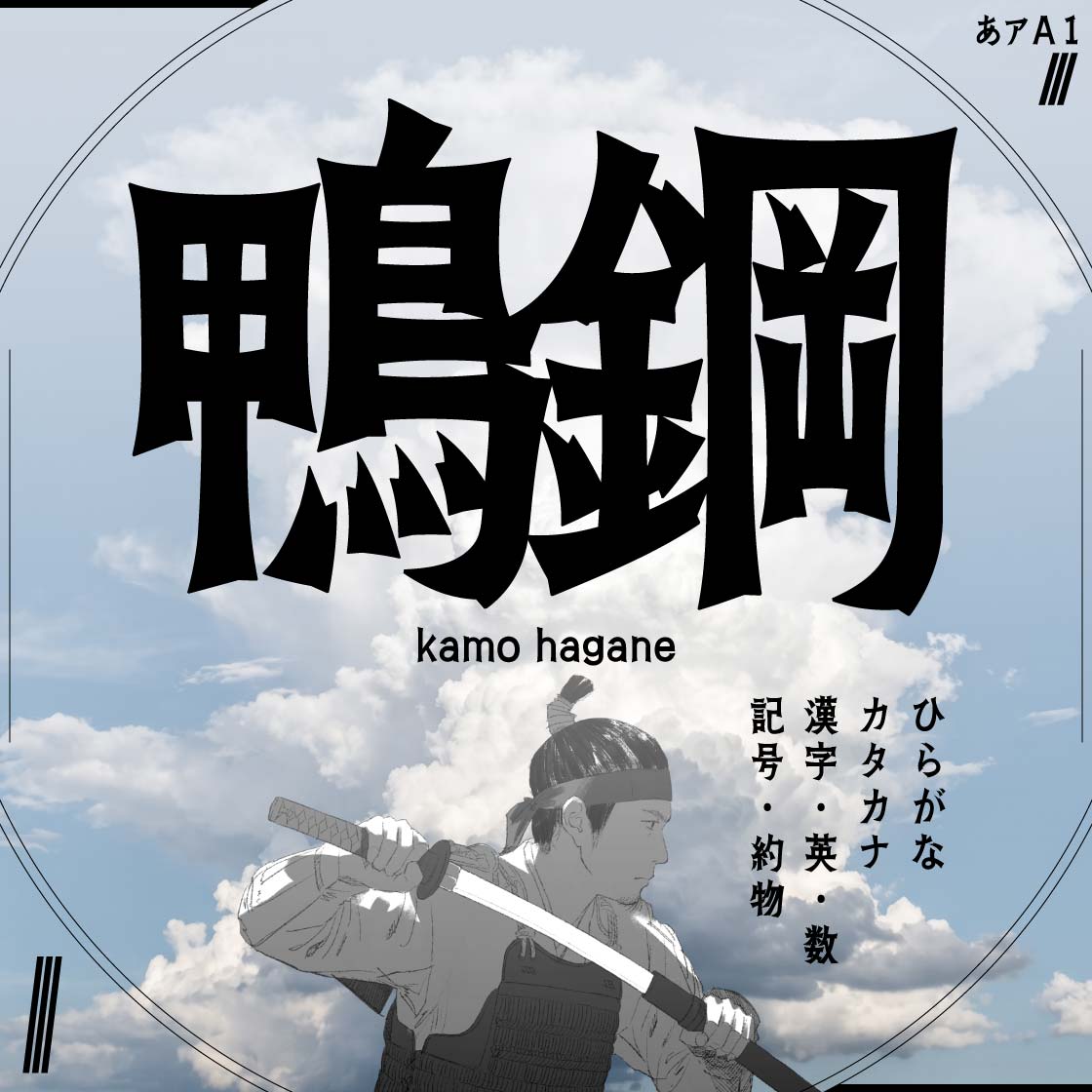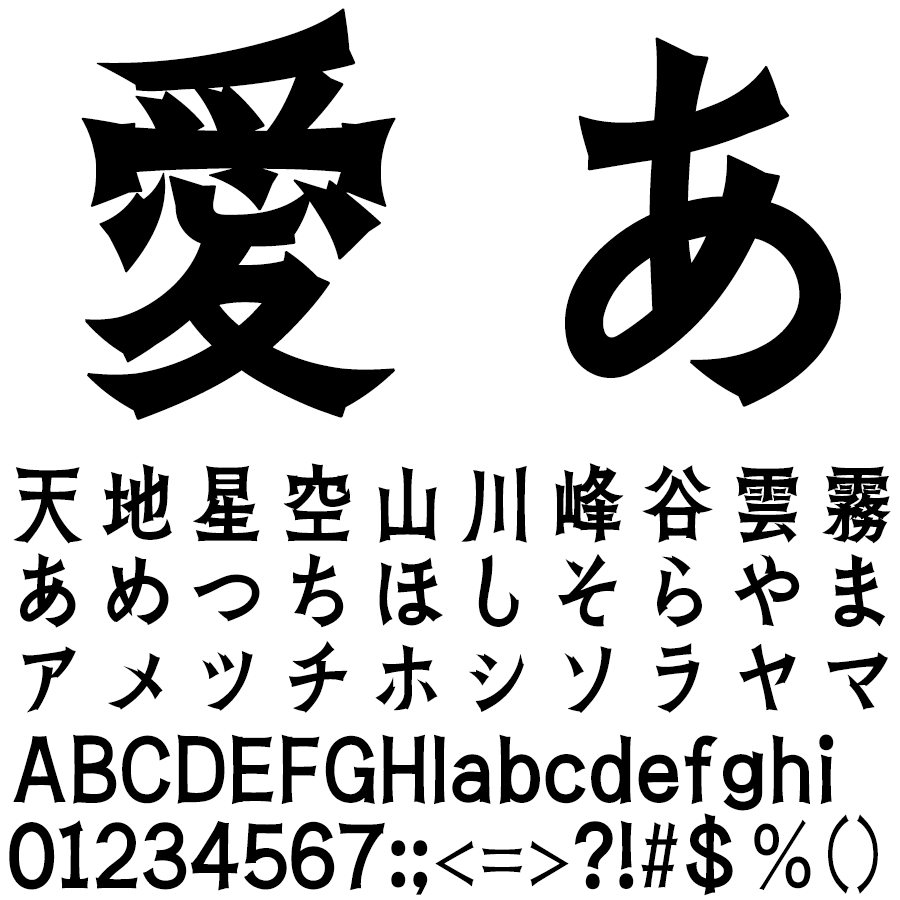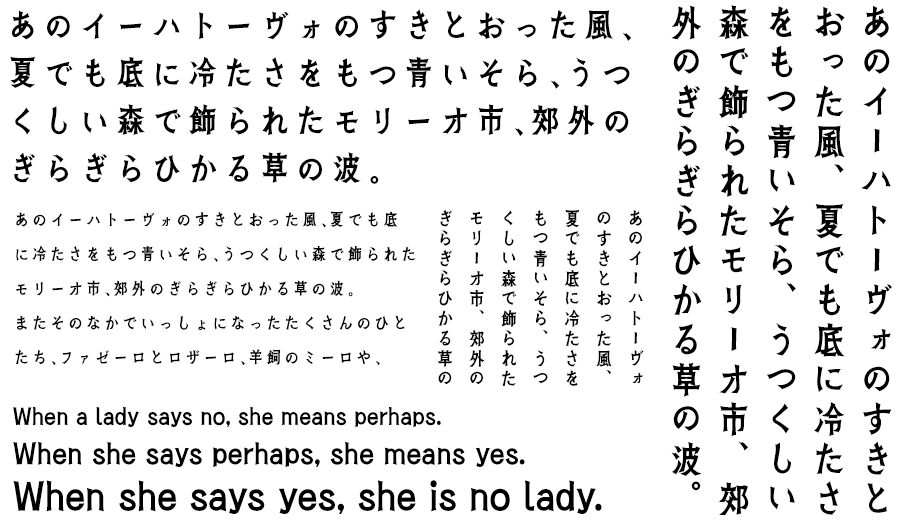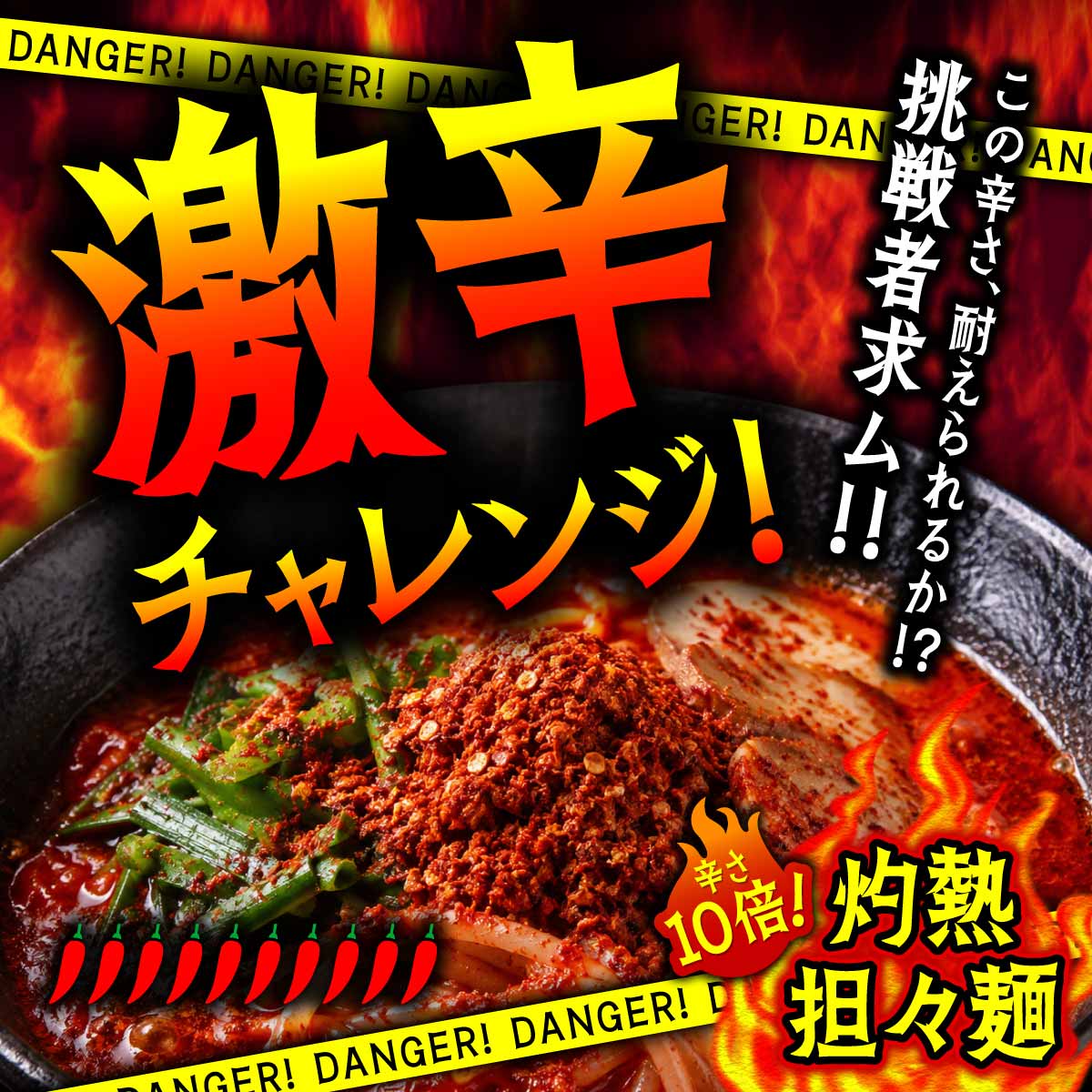
なにも無いところから、なにかを作りたい。今あるモノをもっと良く見せたい。お客様から寄せられる様々な課題をデザインという視点から観察し新たな発見や問題の解決、違った見え方や驚きある体験をご提案することをコンセプトとする「ヤマナカデザインワークス」。
鴨鋼 (かもはがね)
「鴨鋼 (かもはがね)」は明朝体ではなく、筆文字でもない。しかし手書き感のある線運びを持たせることで、有機的な鋭さを表現した日本語フォントです。
スズメボンボン
「スズメボンボン」は、ヤマナカデザインワークスにとってのスタンダードとして制作した、コミカルで可愛く、扱いやすい日本語フォントです。
ネコノコラヂヲ
「ネコノコラヂヲ」は、レトロ・エレガンスをテーマとして、装飾的な猫脚をデザインソースに制作した日本語フォントです。今尚現代のクリエイターに影響を与え続ける「明治・大正」の頃のクリエイティブへの憧れを詰め込みました。見出しやタイトル、ロゴなどに是非お使いください。
ブルズドーナツ
「ブルズドーナツ」は、コロコロ転げ回るフレンチブルドックをイメージして作った日本語フォントです。見出しやタイトル、ロゴなどに丸くてかわいい印象を持たせたいときに是非お使いください。
ティラノゴチ
手書き文字をベースとして、やんちゃ小僧をコンセプトに作った元気系日本語フォントです。見出しやタイトル、ロゴなどにインパクトを持たせたいとき、力強く元気な印象を持たせたいときに是非お使いください。
金魚ランタン
ブラックレター体を日本語の文字として解釈しなおして設計した日本語フォント。欧文・数字は日本語での解釈を元に再設計しているので、本来のブラックレター体とはまた違った印象となっています。強く鋭い印象を持たせたいとき、世界観を強調したい時に是非お使いください。
やわらかドラゴン
力強くもあり、どこか柔らかい。そんなイメージの日本語フォントです。インパクトを持たせたい時、優しい印象を持たせたい時に。色々な使い方を試してみてください!
かなりあ
かなりあは小さくコロコロとした小鳥のイメージで、字体を崩しすぎず、あらゆる場面で使えるシルエットを目指し作成しました。少し真面目で、でもかわいい日本語フォントです。
ぱぐのみんちょ
ぱぐのみんちょはゆるい感じの日本語フォントです。全グリフが変則的なサイズをしているので、仮名はプロポーショナル化してベタうちした際になるべく自然に見えるようにしています。
プぷプ
プぷプは、ちょっとかわいい、だいぶ丸いフォントです。小学校で習う漢字1000文字を収録しているので、日常会話程度はカバーできます!元々コミックのタイトル用に作成したフォントですので、タイトルや見出し、注目してほしい部分に効果的にご使用いただければと思います。
きなりゴシック
きなりゴシックは華奢で有機的なシルエットのフォントです。日本的でささやかな線表現を出すために作成したフォントですので、繊細で優しい雰囲気を表現したい際に活用できます。
こまどり+
こまどり+は小さくかわいい小鳥のイメージで作成した日本語フォントです。本文よりも、ちょっとした言葉や見出しに使っていただくと、紙面がカワイイ雰囲気になります。 色々な使い方を試してください!
バンバン
バンバンという音から賑やかで弾けるようなイメージを元に作成したフォントです。四角に近い形状ですが、下に行くにつれ細くなる線、角の丸みを合わせて、丸く柔らかい印象に仕上げています。元々コミックのタイトル用に作成したフォントですので、タイトルや見出し、注目してほしい部分に効果的にご使用いただければと思います。